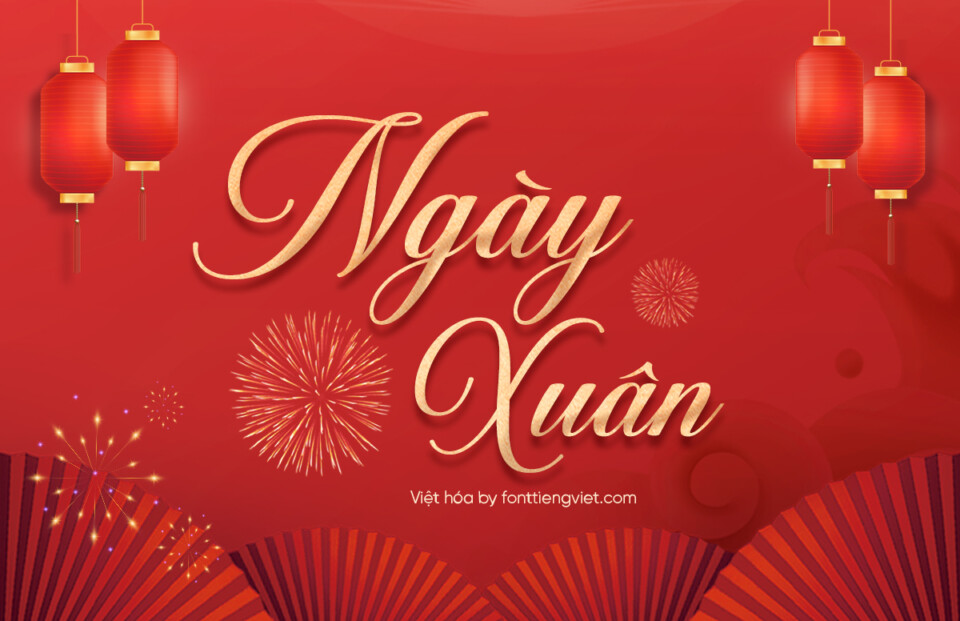
Chào đón một năm mới an lành và tràn đầy hy vọng, việc chuẩn bị cho những thiết kế mang đậm không khí Tết trở nên quan trọng hơn bao giờ hết. Và để tạo nên những tác phẩm đồ họa độc đáo, ấn tượng, không thể không nhắc đến sự góp mặt của những bộ Font Chữ đặc biệt. Trong số đó, Font Việt hóa 1FTV VIP Peristiwa – Font Tết nổi bật như một lựa chọn hoàn hảo, mang đến vẻ đẹp truyền thống pha lẫn nét hiện đại, giúp bạn truyền tải trọn vẹn tinh thần của ngày Tết Nguyên Đán. Bộ font này không chỉ là một công cụ thiết kế mà còn là một tác phẩm nghệ thuật, kết nối người dùng với văn hóa và phong tục tập quán của dân tộc thông qua từng nét chữ. Nó thực sự là một làn gió mới cho ngành thiết kế đồ họa Việt Nam, đặc biệt trong những dịp lễ hội quan trọng như Tết Nguyên Đán.
Font Việt hóa 1FTV VIP Peristiwa – Font Tết: Điểm Nhấn Cho Thiết Kế Xuân Đầy Ý Nghĩa
Bộ font Font Việt hóa 1FTV VIP Peristiwa – Font Tết mang trong mình một câu chuyện thú vị ngay từ cái tên. “Peristiwa” trong tiếng Indonesia có nghĩa là “sự kiện” hoặc “biến cố”, gợi lên sự kiện trọng đại, những khoảnh khắc đáng nhớ. Khi được Việt hóa và kết hợp với tinh thần Tết, nó không chỉ đơn thuần là một kiểu chữ mà còn là biểu tượng của những sự kiện văn hóa quan trọng nhất trong năm của người Việt. Mỗi đường nét của font đều được chăm chút tỉ mỉ, từ độ dày, độ nghiêng cho đến các chi tiết trang trí nhỏ, tất cả đều toát lên vẻ sang trọng, truyền thống nhưng vẫn rất hiện đại và dễ ứng dụng. Sự kết hợp hài hòa giữa yếu tố cổ điển và đương đại giúp font chữ này trở nên linh hoạt, phù hợp với nhiều phong cách thiết kế khác nhau, từ tối giản đến cầu kỳ, phức tạp.
Sức Hút Đặc Biệt Từ Tên Gọi “Peristiwa” Và Quá Trình Việt Hóa Tinh Tế
Cái tên “Peristiwa” vốn đã mang một ý nghĩa sâu sắc về sự kiện, về những điều đáng nhớ. Khi được một cách khéo léo Việt hóa, bộ font này không chỉ giữ lại được tinh thần ban đầu mà còn được thổi hồn văn hóa Việt, đặc biệt là không khí của những ngày Tết. Quá trình Việt hóa không chỉ dừng lại ở việc bổ sung các dấu tiếng Việt mà còn điều chỉnh tỉ mỉ từng ký tự để đảm bảo tính thẩm mỹ, dễ đọc và phù hợp với ngữ cảnh tiếng Việt. Điều này đòi hỏi sự tinh tế và am hiểu sâu sắc về cả typographic lẫn văn hóa bản địa. Nhờ vậy, Font Việt hóa 1FTV VIP Peristiwa – Font Tết trở thành một công cụ đắc lực cho các nhà thiết kế muốn truyền tải thông điệp về Tết Nguyên Đán một cách chân thực và sống động nhất, tạo nên những sản phẩm đồ họa không chỉ đẹp mắt mà còn giàu ý nghĩa.
Tại Sao Lại Là “Font Tết” Và Vai Trò Của Nó Trong Các Thiết Kế Mùa Lễ Hội?
Được mệnh danh là “Font Tết”, bộ font này sở hữu những đặc điểm hình thái và cảm xúc rất phù hợp với không khí lễ hội truyền thống của Việt Nam. Nó thường được thiết kế với các đường nét mềm mại, uyển chuyển, đôi khi có thêm các chi tiết cách điệu mô phỏng hoa mai, hoa đào, hoặc những họa tiết truyền thống khác. Mục tiêu là gợi lên sự ấm cúng, sum vầy, may mắn và thịnh vượng – những giá trị cốt lõi của ngày Tết. Việc sử dụng Font Việt hóa 1FTV VIP Peristiwa – Font Tết trong các thiết kế như thiệp chúc mừng, lì xì, banner quảng cáo hay bao bì sản phẩm mùa Tết sẽ ngay lập tức tạo ra một cảm giác thân thuộc, gần gũi và đầy tính lễ hội. Nó giúp sản phẩm của bạn nổi bật hơn, thu hút sự chú ý và để lại ấn tượng sâu sắc trong lòng người xem, góp phần lan tỏa niềm vui và sự lạc quan của năm mới đến mọi nhà.
Ứng Dụng Đa Dạng Của Font Việt Hóa 1FTV VIP Peristiwa – Font Tết Trong Cuộc Sống
Không chỉ dừng lại ở việc mang ý nghĩa sâu sắc, Font Việt hóa 1FTV VIP Peristiwa – Font Tết còn có tính ứng dụng rất cao, phù hợp với nhiều loại hình sản phẩm và ấn phẩm khác nhau, đặc biệt trong mùa Tết. Sự linh hoạt trong thiết kế giúp nó dễ dàng kết hợp với các yếu tố đồ họa khác, tạo nên tổng thể hài hòa và chuyên nghiệp. Từ những sản phẩm in ấn truyền thống cho đến các ấn phẩm kỹ thuật số, bộ font này đều có thể phát huy tối đa vẻ đẹp và công năng của mình, giúp bạn tạo ra những sản phẩm độc đáo và mang đậm dấu ấn cá nhân. Nó không chỉ là công cụ mà còn là nguồn cảm hứng bất tận cho những người yêu thích sáng tạo và muốn thể hiện cá tính riêng.
Trong Thiết Kế Thiệp Chúc Mừng Năm Mới Và Lì Xì Độc Đáo
Thiệp chúc mừng và lì xì là những món quà không thể thiếu trong dịp Tết. Sử dụng Font Việt hóa 1FTV VIP Peristiwa – Font Tết để in lên những tấm thiệp này sẽ tạo nên sự sang trọng, tinh tế và mang đậm nét truyền thống. Những lời chúc phúc, câu đối Tết sẽ trở nên ý nghĩa hơn khi được thể hiện bằng một phông chữ đẹp mắt và phù hợp. Bộ font giúp làm nổi bật thông điệp, tạo cảm giác trân trọng và thể hiện sự đầu tư của người tặng. Từng chi tiết trên thiệp hay bao lì xì đều trở nên sống động hơn, thu hút ánh nhìn và gợi lên cảm xúc tích cực cho người nhận, biến những vật phẩm nhỏ bé này thành những tác phẩm nghệ thuật thực sự.
Cho Banner, Poster Quảng Cáo Tết Và Các Ấn Phẩm Truyền Thông
Trong lĩnh vực quảng cáo, việc tạo ra những ấn phẩm thu hút là chìa khóa thành công. Font Việt hóa 1FTV VIP Peristiwa – Font Tết với vẻ đẹp độc đáo và ấn tượng sẽ giúp các banner, poster, và ấn phẩm truyền thông của bạn nổi bật hơn trong mùa Tết. Nó không chỉ thu hút ánh nhìn mà còn truyền tải được không khí lễ hội một cách rõ ràng và mạnh mẽ. Từ các chương trình khuyến mãi, sự kiện Tết cho đến thông điệp chúc mừng năm mới từ doanh nghiệp, bộ font này đều có thể giúp bạn tạo ra hiệu ứng thị giác mạnh mẽ, dễ dàng đi vào lòng người xem và ghi nhớ. Đây là yếu tố quan trọng để thương hiệu của bạn được nhận diện và yêu mến trong dịp đặc biệt này.
Các Sản Phẩm Trang Trí, Đồ Lưu Niệm Và Thiết Kế Bao Bì Mùa Lễ Hội
Ngoài ra, bộ font này còn rất phù hợp để ứng dụng vào các sản phẩm trang trí nhà cửa, đồ lưu niệm hay thiết kế bao bì cho các sản phẩm mùa Tết. Từ tranh treo tường, câu đối, đồ handmade cho đến hộp quà Tết, việc sử dụng Font Việt hóa 1FTV VIP Peristiwa – Font Tết sẽ làm tăng thêm giá trị thẩm mỹ và nét đặc trưng văn hóa cho sản phẩm. Nó không chỉ giúp sản phẩm đẹp hơn mà còn kể được câu chuyện về Tết Việt, về những giá trị truyền thống tốt đẹp. Điều này giúp các sản phẩm không chỉ là vật phẩm mà còn là một phần của trải nghiệm văn hóa, mang đến niềm vui và sự hoài niệm cho người tiêu dùng trong những ngày đầu năm mới.
Tổng kết lại, Font Việt hóa 1FTV VIP Peristiwa – Font Tết không chỉ là một bộ Font Chữ đơn thuần mà còn là một công cụ mạnh mẽ, giúp các nhà thiết kế và những người yêu sáng tạo thể hiện tài năng của mình trong mùa Tết. Với vẻ đẹp tinh tế, sự linh hoạt trong ứng dụng và khả năng truyền tải cảm xúc mạnh mẽ, bộ font này chắc chắn sẽ là “trợ thủ” đắc lực, góp phần làm nên những tác phẩm nghệ thuật đồ họa đáng nhớ, mang đậm dấu ấn cá nhân và tinh thần Tết Việt. Hãy cùng khám phá và biến những ý tưởng của bạn thành hiện thực với bộ font tuyệt vời này!